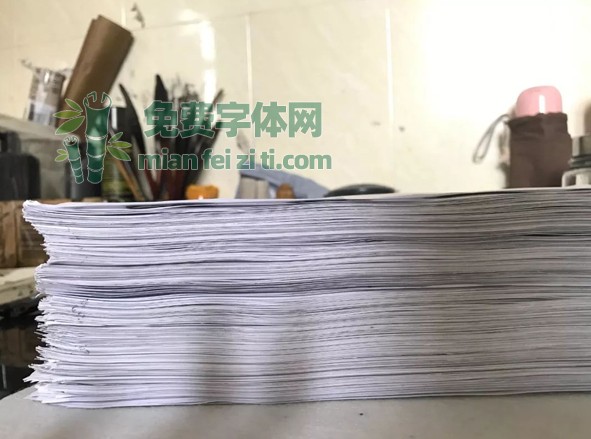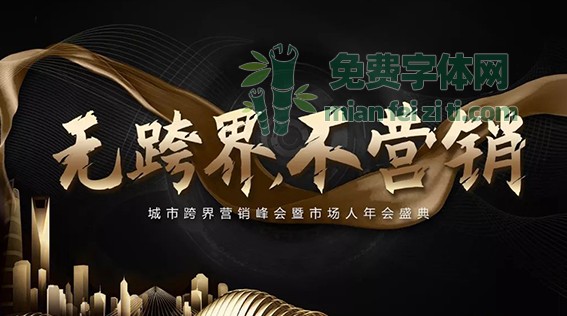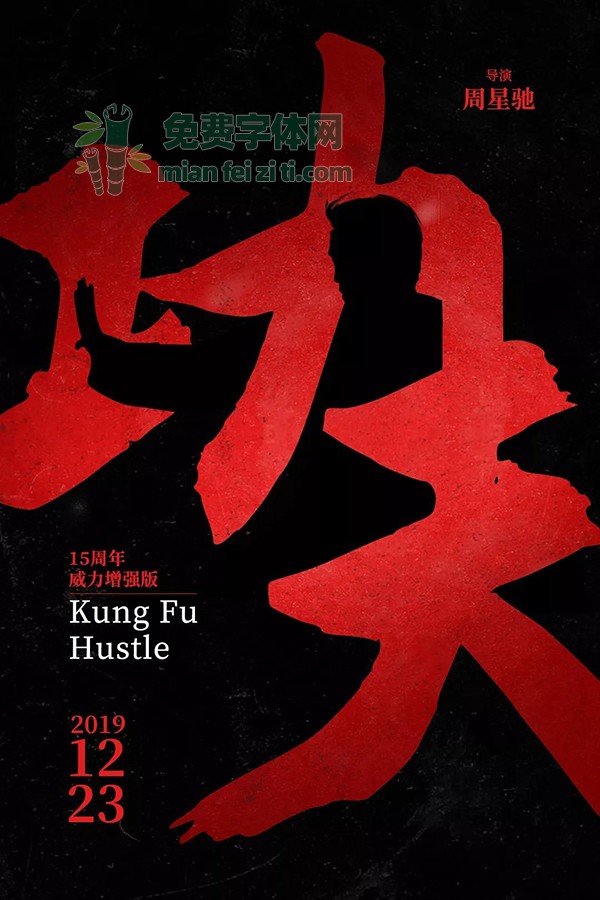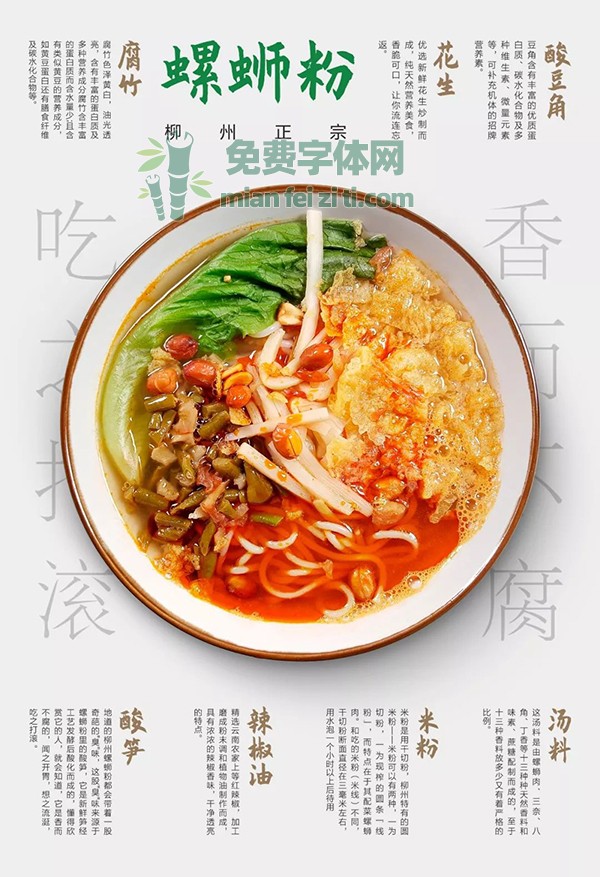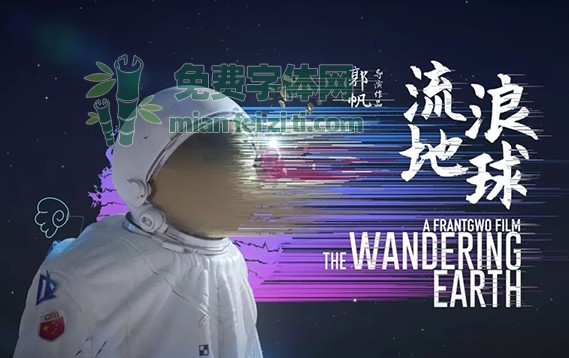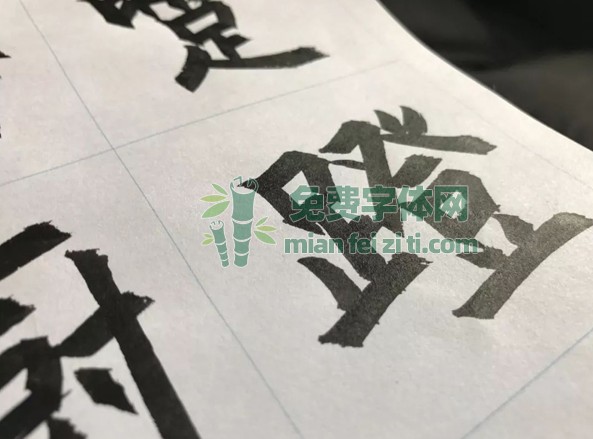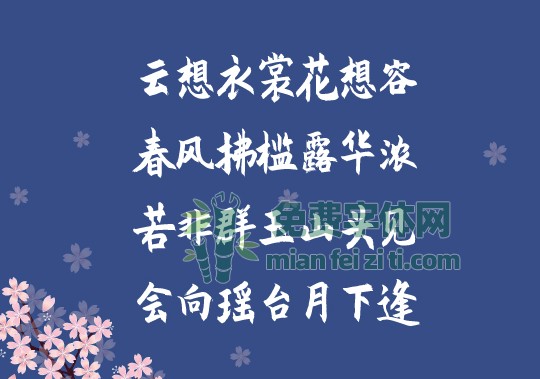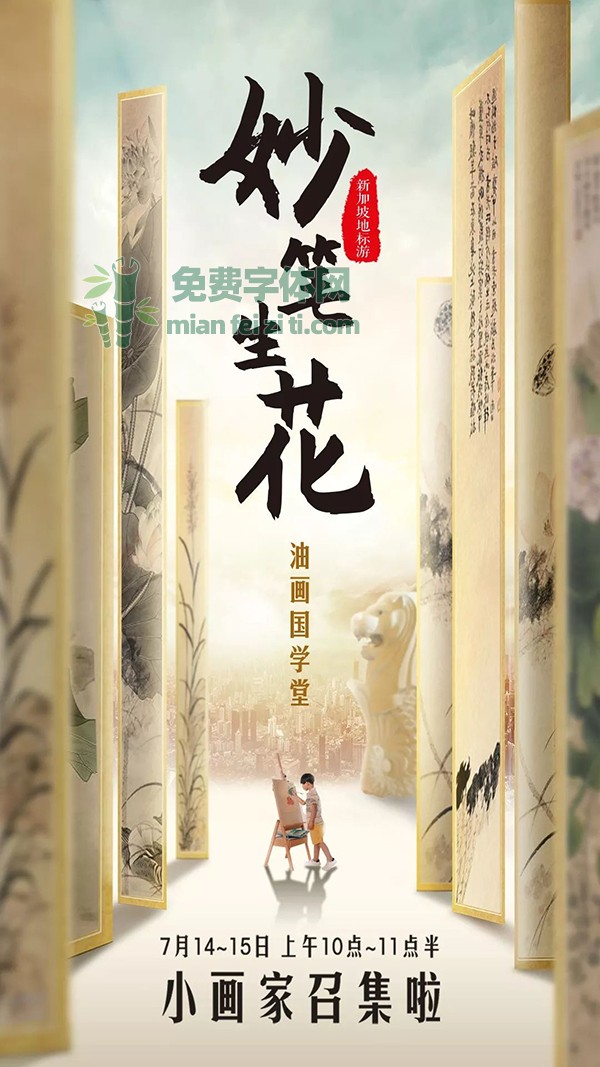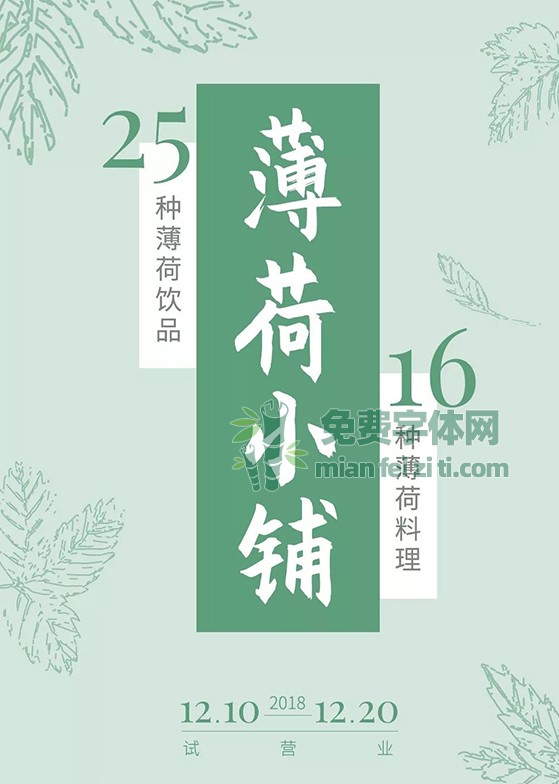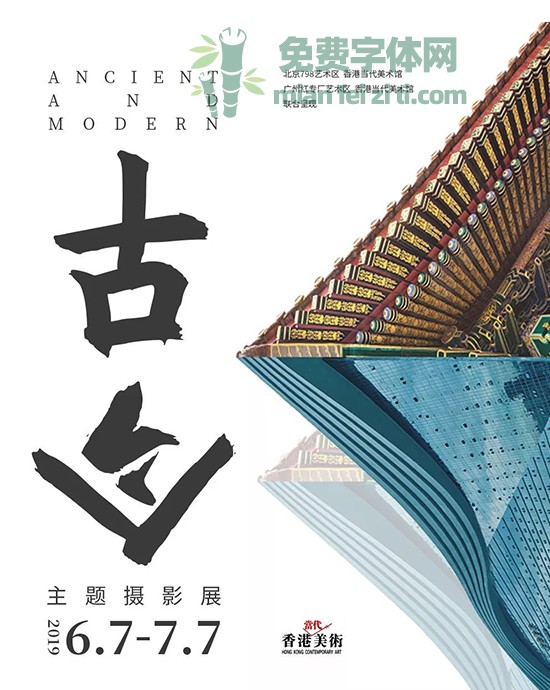
可以完全免费商用的毛笔字体免费下载-庞门正道粗书体
很多群里的小伙伴时不时的都会问,有没有免费的毛笔字体可用,今天终于出了一款,记住这是第一款免费可商用的毛笔字体,由车港同学手写数月,并由阿门大神出资制作总耗时9个月完成,共计6000多个汉字,目前只支持简体。商用免费的!商用免费的!商用免费的!重要的事情说三遍,葱花昨日看到这个消息即兴奋又感动,不计报酬倾情奉献的精神值得我们所有的设计师学习。
这个毛笔字体的名字就是-庞门正道粗书体
车同学每天早起写100字,然后才去上班,下面是一些手稿,真的是勤奋的孩纸让人喜欢。
车同学说由于都是白色的铜板纸张,打好的格子,失去了很多细节,尤其是飞白,但是对于不会写字的葱花来说已经很好了,主要是免费商用哦,全球唯一一款呢。
下面上图展示一下这个字体的形象以及应用场景